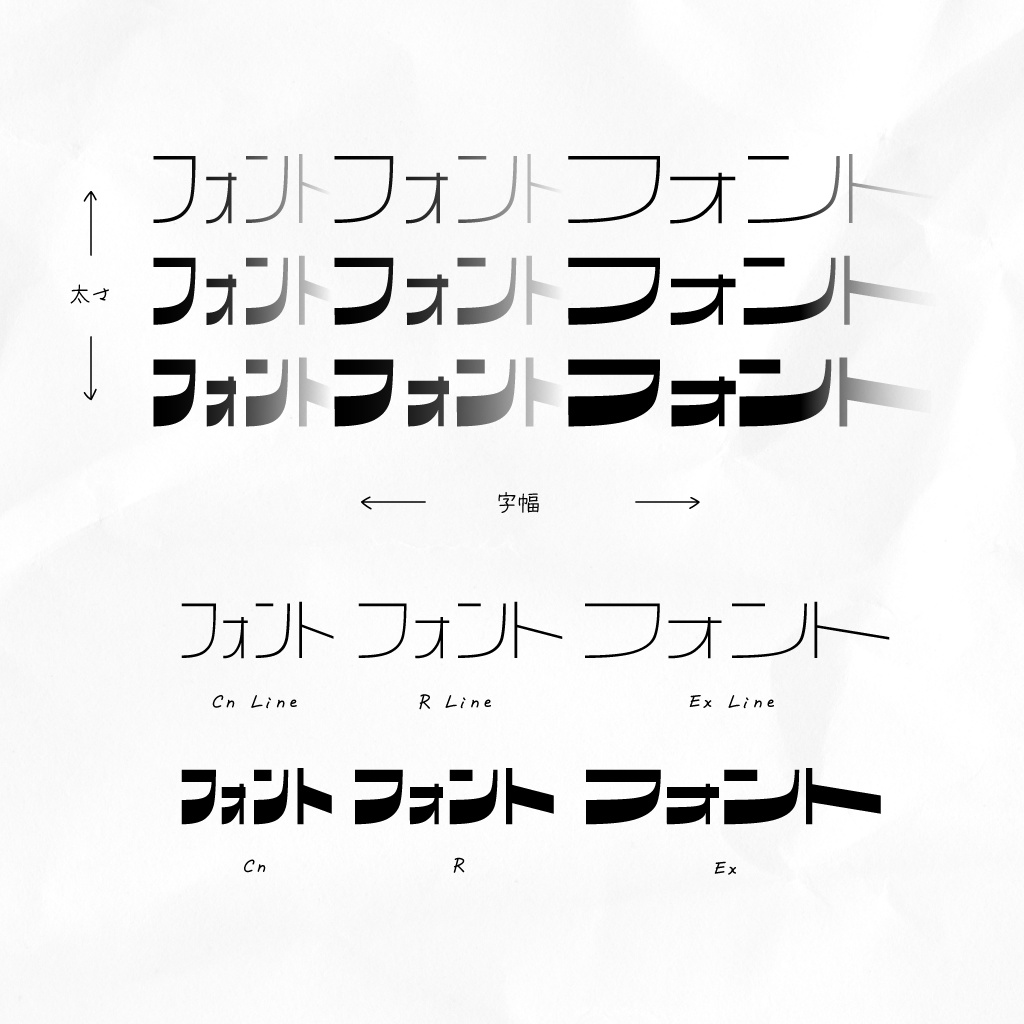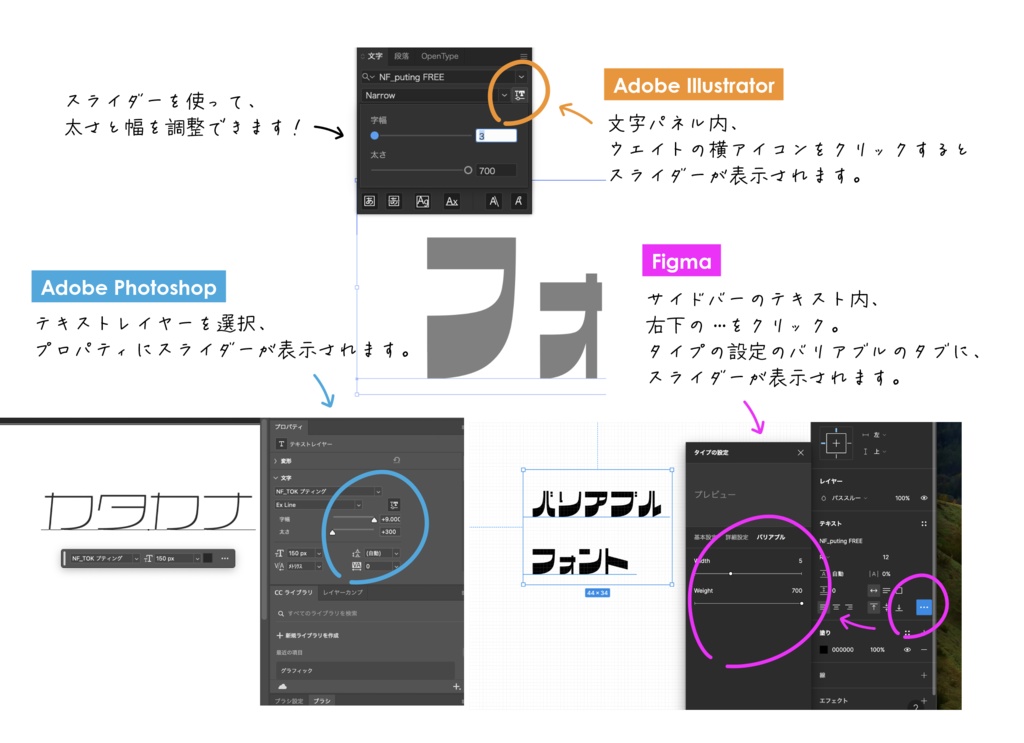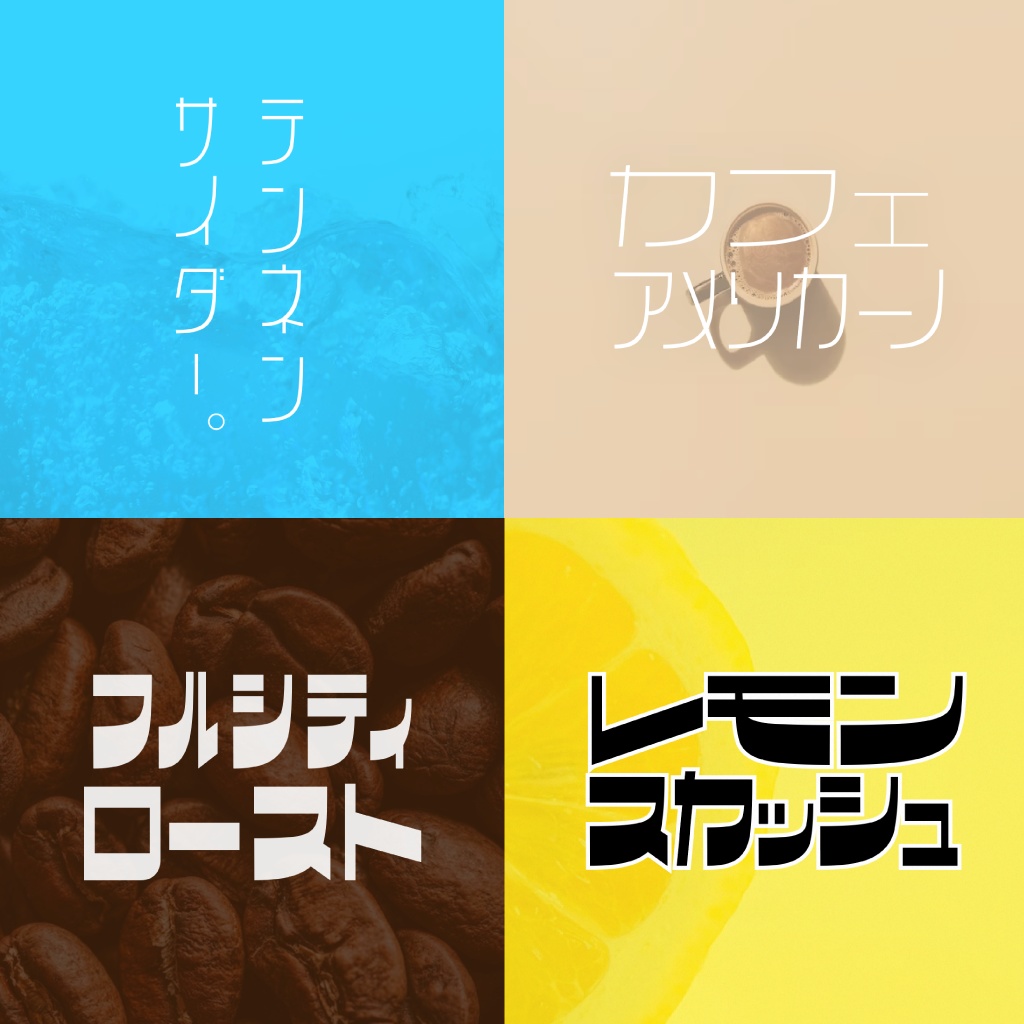
カタカナのバリアブルフォント|プティング Free
太さと字幅を連続的に変化させられる、 カタカナのバリアブルフォントです! 「日本語デザイン書体のバリアブル(可変)フォントって、見かけないなー」と思い制作しました。 【バリアブルフォントに関して】 バリアブルフォントは、 対応しているアプリケーションにてフルで動作します。 対応していないアプリケーションでは、 予め設定されたウエイトのみ使用できるなど制限があります。 対応アプリケーション: Adobe illustrator, Photoshop, Figma, Cavalry ...等 【収録文字】 カタカナといくつかの記号 --- アイウエオカキクケコサシスセソタチツテトナニヌネノハヒフヘホマミムメモヤヰユヱヨラリルレロワヲン ガギグゲゴザジズゼゾダヂヅデドバビブベボパピプペポヷヸヹヺヴァィゥェォヵヶッャュョヮ ー、。?! 【収録データ】 ・無料版:バリアブルフォント(VF.ttf) ・コーヒーをおごる(投銭版):VF.ttf + R・R Line・Cn・Cn Line・Ex・Ex Line.otf 【フォントの利用について】 ・個人利用可(公序良俗に反しない範囲でお願いします!) ・X(Twitter)のアカウント(@toktaro)をフォローすると、商用利用できます。 ※Xアカウントがない場合は、BoothアカウントのフォローでもOKです。 とくたろ(@toktaro) / X: https://twitter.com/toktaro 【禁止事項】 ・当フォントを利用した制作物、ロゴなどの商標登録 ・フォントデータの自作発言・無断転載・再配布・販売 ・サーバー・チャット・SNS等で、他者がダウンロード出来る状態にすること。 --- ※著作権はすべて、制作者とくたろに属します。 ※フォントを使用して発生した、いかなるトラブル・損害について一切責任を負いません。 ※フォントデータをダウンロードした時点で、利用について・禁止事項等、記載内容に同意したこととします。 ※上記内容は予告なく変更する場合がございます。あらかじめご了承ください。